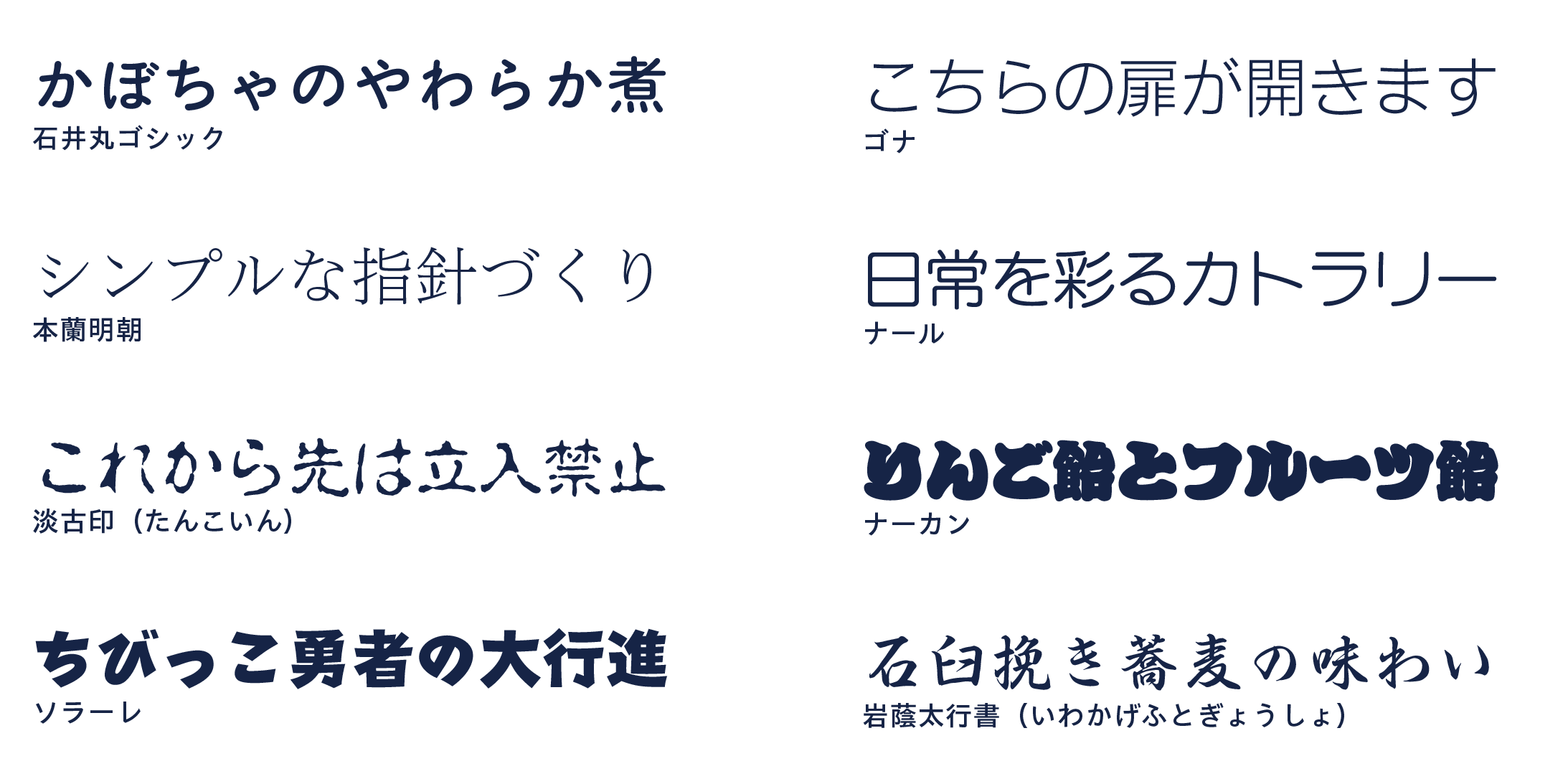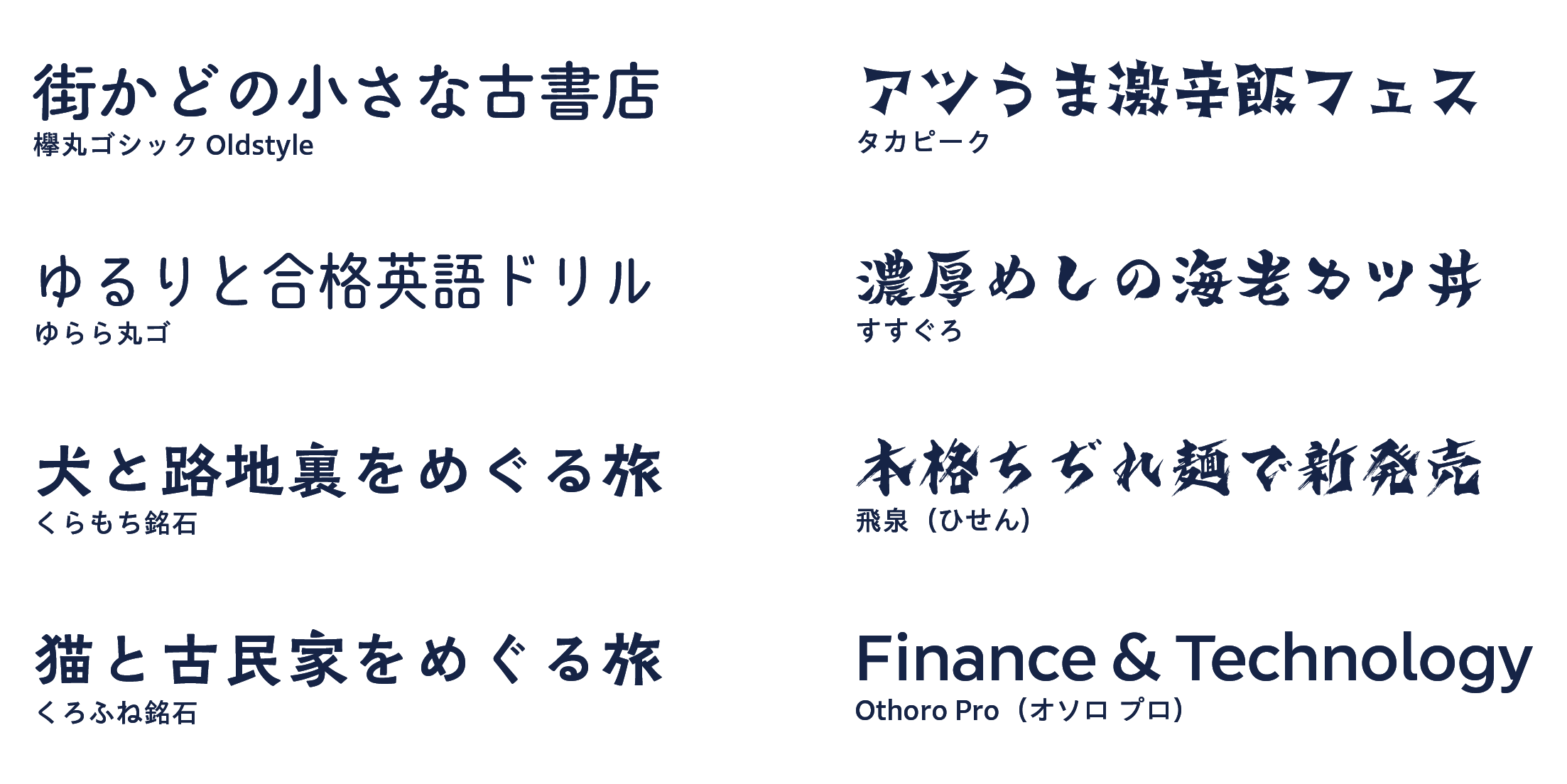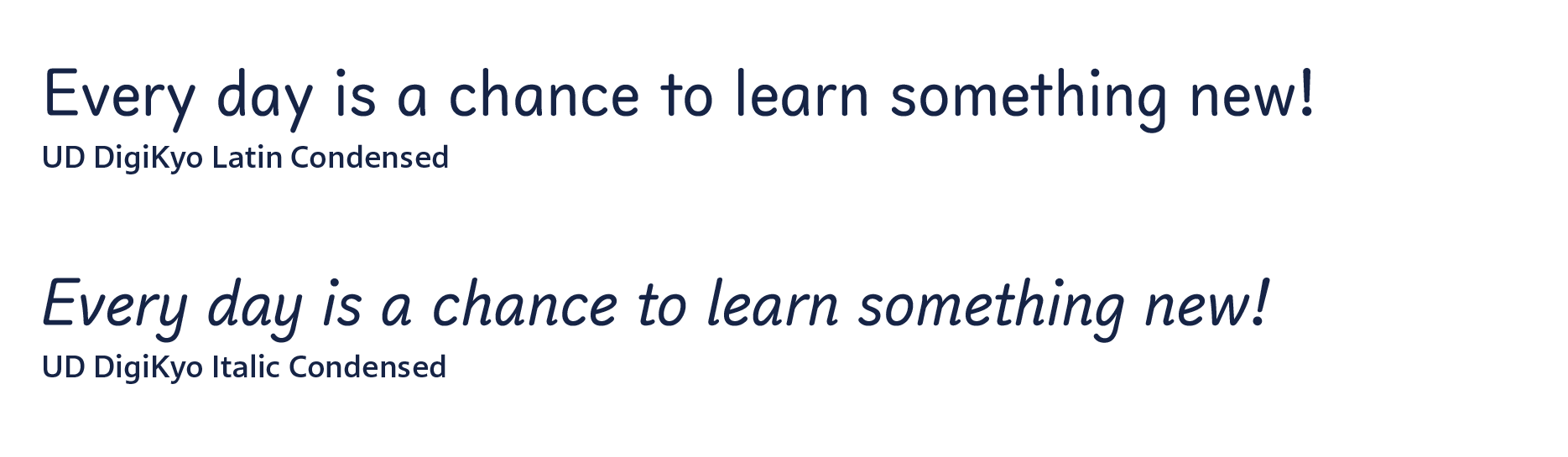
モリサワ 2026年度新書体として「石井丸ゴシック」や「本蘭明朝」など写研フォント、欅シリーズの新ラインナップ「欅丸ゴシック Oldstyle」など35ファミリーをリリース〜10月14日から提供開始〜
株式会社モリサワ(代表取締役社長:森澤彰彦 本社:大阪市浪速区敷津東2-6-25 Tel:06-6649-2151 代表、以下モリサワ)は、フォントサブスクリプションサービス「Morisawa Fonts」で提供する2026年度新書体として、「石井丸ゴシック」や「本蘭明朝」など写研フォントに加え、欅(けやき)シリーズの新ラインナップ「欅丸ゴシック Oldstyle」など和文ゴシック体やデザイン書体、多言語書体など合計35ファミリーをリリースします。提供開始は2026年10月14日(水)14時の予定です。
2026年度新書体では、株式会社写研(代表取締役社長:笠原義隆 本社:東京都豊島区南大塚2-35-2、以下写研)とのOpenTypeフォント開発プロジェクトから、写研フォント21ファミリーがラインナップに加わります。オリジナル書体の優美さを残しつつ現代の環境や用途に合わせてリデザインする「改刻フォント」として、写研の創業者・石井茂吉氏のデザインをベースにしたオールドスタイルの丸ゴシック体「石井丸ゴシック」と、明瞭なデザインの中に伝統的な筆のニュアンスを感じさせるモダンスタイルの明朝体「本蘭明朝」の2ファミリーを追加します。また、写研から提供を受けたアウトラインデータをもとに不足文字の追加など仕様を整理した「写研クラシックス」には、伝統的な骨格ににじみやかすれを組み合わせた「淡古印(たんこいん)」や今回初公開となる切り絵風のデザイン書体「ソラーレ」など17ファミリーが仲間入りします。「ゴナ」「ナール」2ファミリーに新たなウエイトも追加し、より幅広い用途に対応できるようになります。
さらにこれらのほか、新たなモリサワフォントとして和文ゴシック体・丸ゴシック体やデザイン書体、多言語書体など12ファミリーを追加し、フォントライブラリを拡充します。欅シリーズには、オールドな雰囲気を持つ丸ゴシック体「欅丸ゴシック Oldstyle」が登場。同じコンセプトを持つ欅シリーズの書体と合わせて使用することで、統一感のあるデザイン表現が可能になります。そのほか、手書き風の表情と長体気味のすっきりとしたプロポーションが特徴の丸ゴシック体「ゆらら丸ゴ」、中国晋代の碑文から復刻した漢字書体と、日本の近代活字を復刻した和字(かな)書体を組み合わせたオールドスタイルのゴシック体「くらもち銘石」「くろふね銘石」、遊び心あふれる骨格に極端なフレアを描くストロークが特徴の「タカピーク」、力強さや勢いのあるデザイン筆書体「すすぐろ」「飛泉(ひせん)」などを追加します。加えて幾何学的なストロークと均質なプロポーションが特徴の欧文書体「Othoro Pro(オソロプロ)」をはじめ、ハングルや簡体字・繁体字など4ファミリーの多言語書体を追加します。
ほかにも、タイプバンクフォントとして、UDデジタル教科書体の欧文書体「UD DigiKyo Latin Condensed」「UD DigiKyo Italic Condensed」の2ファミリーを追加します。中高生など中級者向けの英語教材におすすめの書体です。